Republish là một dự án mang tính khám phá và thử nghiệm được khởi xướng bởi Behalf Studio, với mong muốn khơi dậy các hình mẫu typographic xưa cũ ẩn giấu đâu đó trong cảnh quan đô thị hiện đại và các tài liệu được lưu trữ, rồi hồi sinh chúng thành các kiểu chữ kỹ thuật số. Republish vừa giới thiệu một số font chữ Việt rất ấn tượng và bạn có thể tải và sử dụng nó miễn phí.
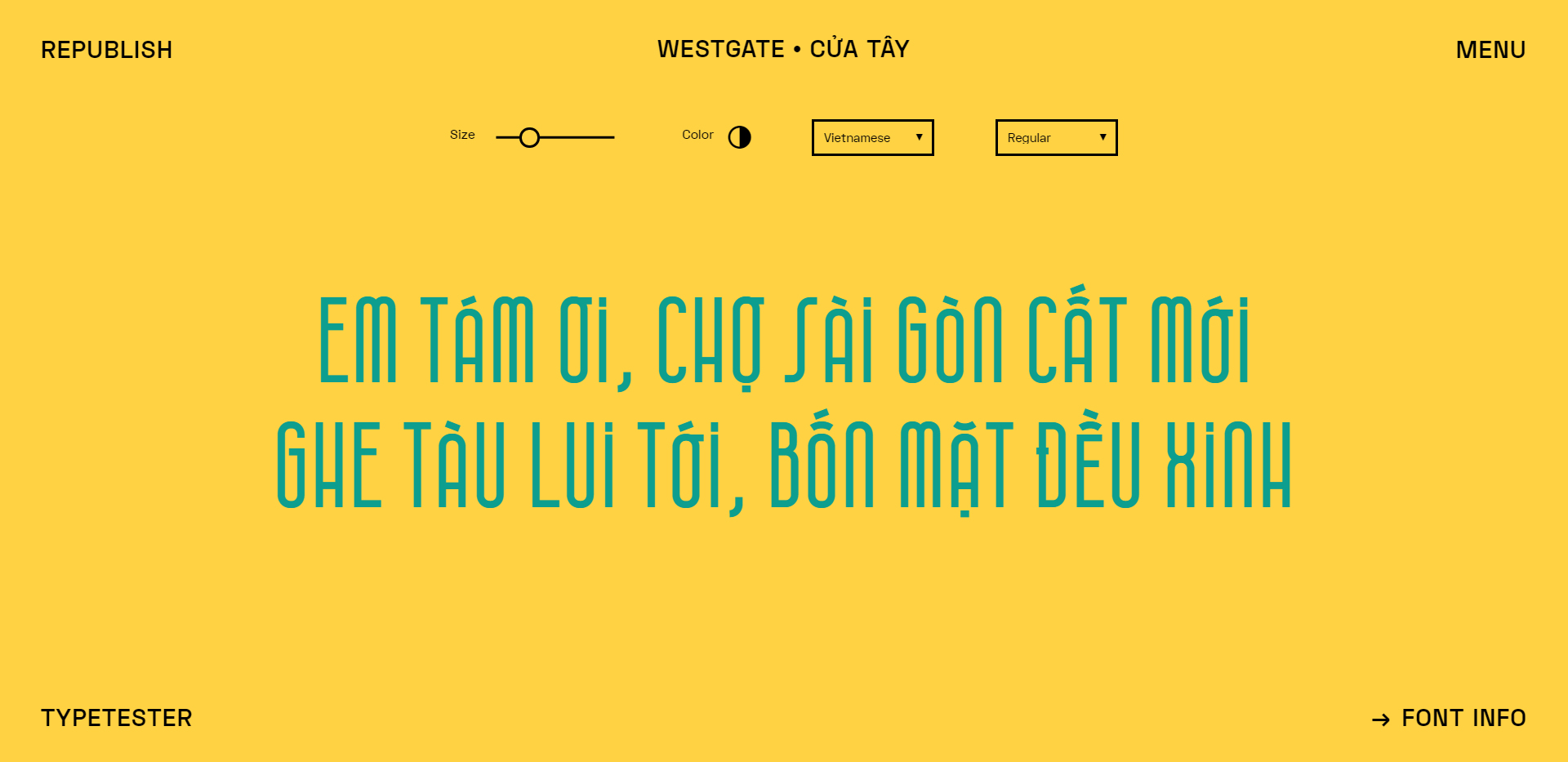
Thành quả của dự án này chính là một bộ sưu tập có chọn lọc các phông chữ miễn phí và mã nguồn mở, cùng với các yếu tố mang tính kể chuyện, được tạo ra bởi người Việt và dành cho người Việt. Đây là nỗ lực của chúng tôi để trả lại tính thẩm mỹ độc đáo nhưng rất quen thuộc của bản sắc địa phương cho cộng đồng.
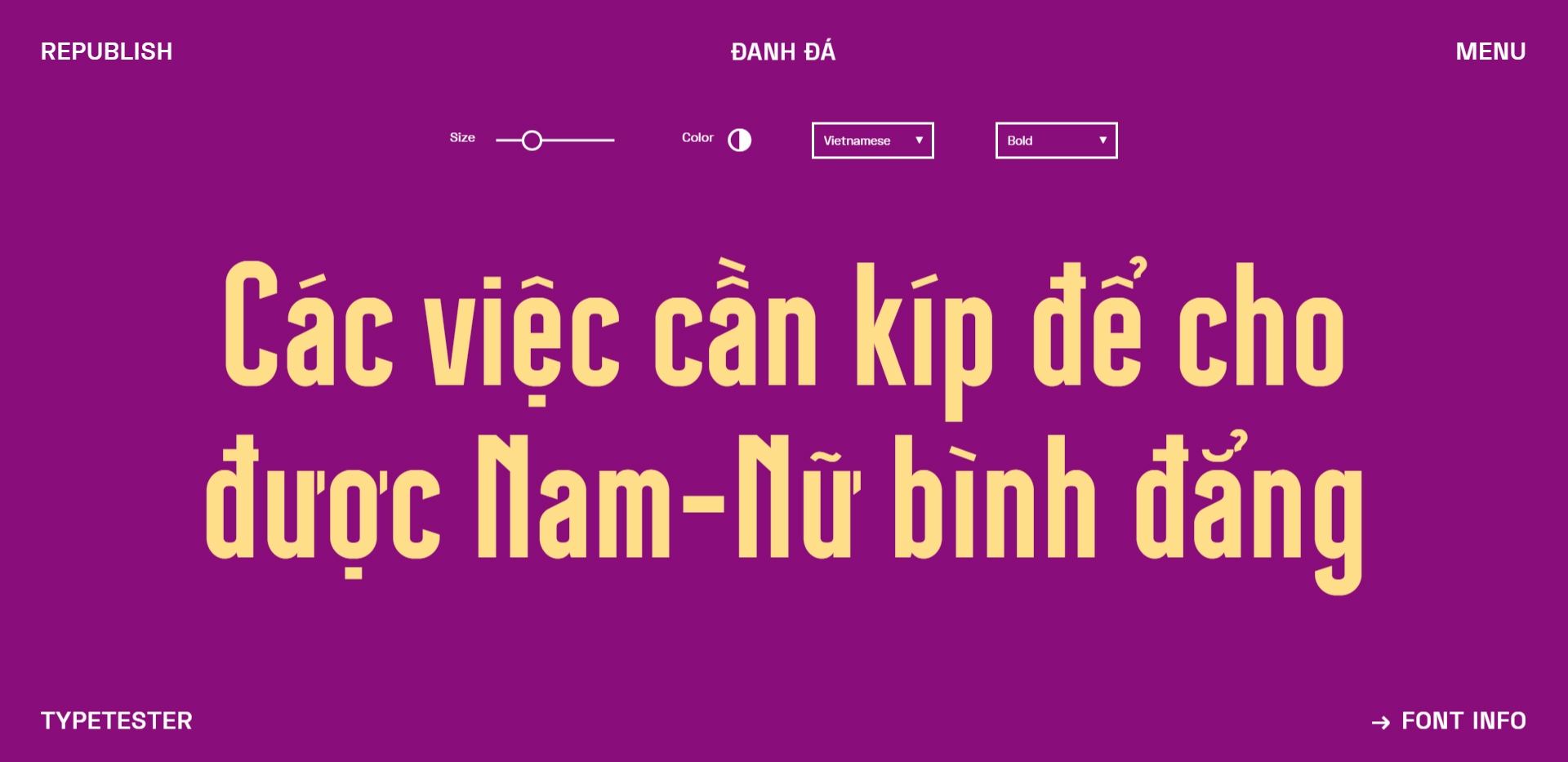
Quá trình tạo ra phiên bản kỹ thuật số này bao gồm cả việc nghiên cứu kỹ lưỡng và thiết kế dựa trên suy đoán. Bắt đầu bằng việc thu thập và nghiên cứu các yếu tố typographic của địa phương, chúng tôi chọn ra các yếu tố có đủ tiềm năng để phát triển và thử nghiệm. Sau đó chúng tôi ngoại suy ra một typeface hoàn chỉnh dựa trên một vài chữ cái, dựa trên nghiên cứu trực quan và bối cảnh văn hóa của chúng.